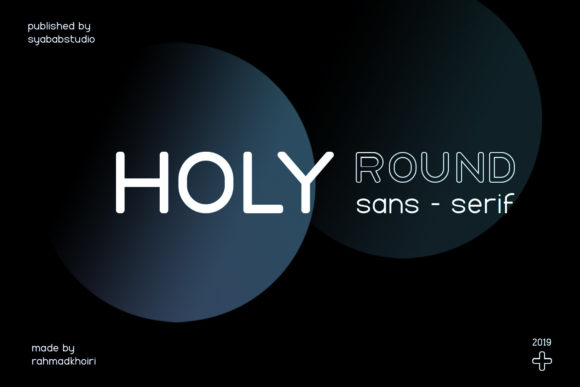
Святой - это минимальный и аккуратный без засечек шрифт.
Его легко подогнать под невероятно большой набор проектов, так что добавьте его к вашим творческим идеям и заметьте, как он выделяет их на фоне других!